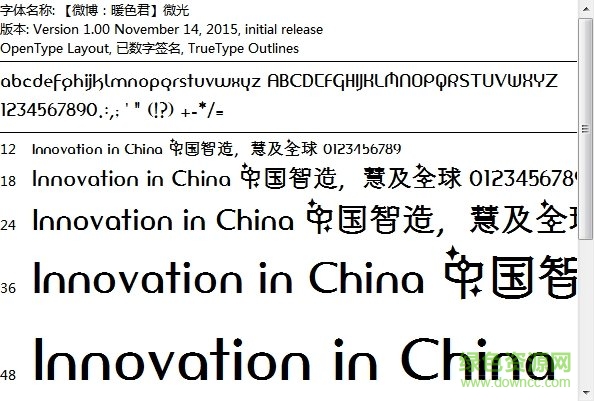
晨光熹微字體
晨光熹微字體,又名暖色君微光字體,是一款樣式圓潤(rùn)而別致的中文梳打字體,部分漢字進(jìn)行了美化修飾,更顯活潑生機(jī),如果你很喜歡,綠色資源網(wǎng)即可免費(fèi)體驗(yàn)哦!
晨光熹微體簡(jiǎn)介
晨光熹微字體又添加了圖案進(jìn)行裝飾,設(shè)計(jì)精美,線條流暢,字型端正,整體效果十分出色。以廣泛應(yīng)用于橫幅標(biāo)語(yǔ)、美術(shù)設(shè)計(jì)、宣傳海報(bào)、ppt、影視制作以及內(nèi)容用字等領(lǐng)域。
暖色君微光字體
晨光熹微體給人明亮而精簡(jiǎn)的外觀,讓文字擁有不一樣的表達(dá)方式,字里行間的各種實(shí)心或空心字符都變得有靈性起來(lái)!